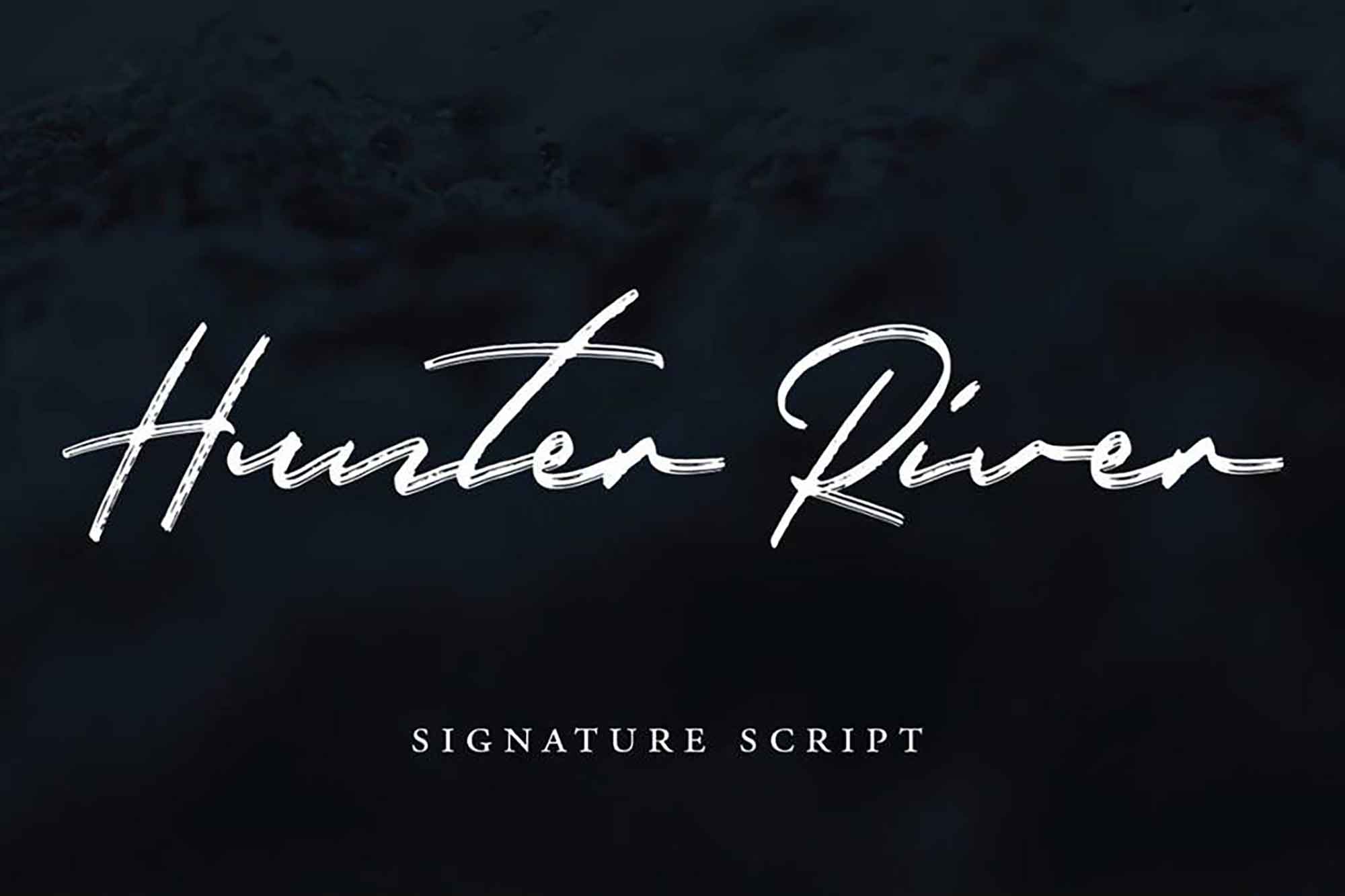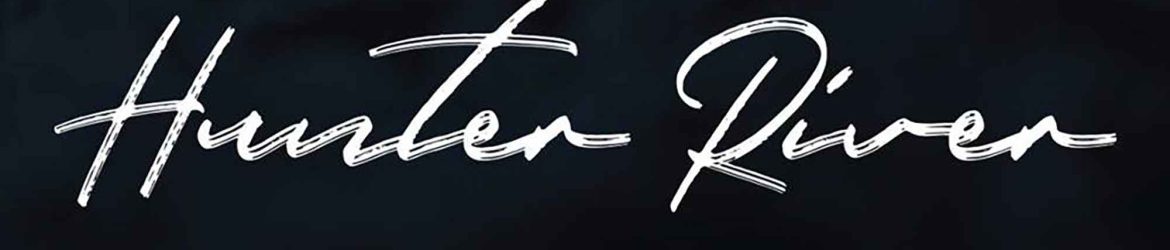
Hunter River Signature Font – Download Grátis
No mundo da tipografia digital, há uma variedade surpreendente de fontes de escrita a mão disponíveis para os designers. Um desses recursos é a Hunter River Signature Font, uma fonte de escrita cursiva ligada que traz uma infusão de autêntica arte e criatividade à sua próxima projeto. Este recurso em particular foi criado para levar uma pitada de personalidade única a qualquer projeto, seja para preservar o encanto de uma pessoa amada, ou transformar a elegância de uma escrita particular em um ativo criativo que pode ser licenciado. Independentemente do motivo, o resultado é um vasto catálogo de fontes de escrita a mão para escolha, criado a partir de incontáveis esforços criativos de designers por todo o mundo. Esta fonte não é apenas uma escolha funcional, é também uma oportunidade para combinar arte e design em um único recurso, trazendo um toque único e memorável a qualquer projeto. É uma forma única de preservar a beleza e a singularidade de uma escrita particular, ou transformá-la em um ativo que pode ser compartilhado e usado para criar mais.